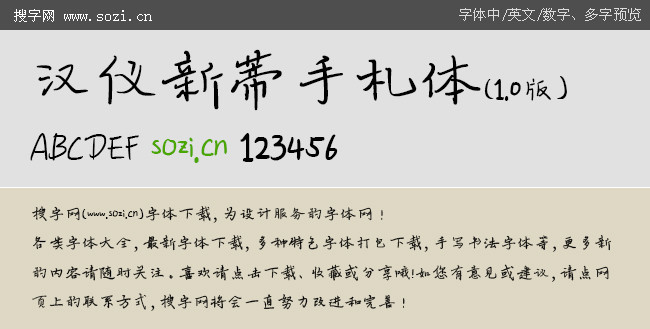
漢儀新蒂手札體1.0
搜字網(wǎng)提供一款漢儀新蒂手札體1.0字體下載,漢儀新蒂手札體是一款漂亮的手寫風(fēng)格書法字體。由漢儀新蒂工作室出品,漢儀新蒂工作室成立于2016年,由漢儀字庫與新蒂字體聯(lián)合成立,本字體字形流暢大方,適合應(yīng)用于海報設(shè)計(jì)、藝術(shù)設(shè)計(jì)、包裝設(shè)計(jì)等應(yīng)用。(本字體為個人非商用版,如需要商用請聯(lián)系漢儀公司購買版權(quán))